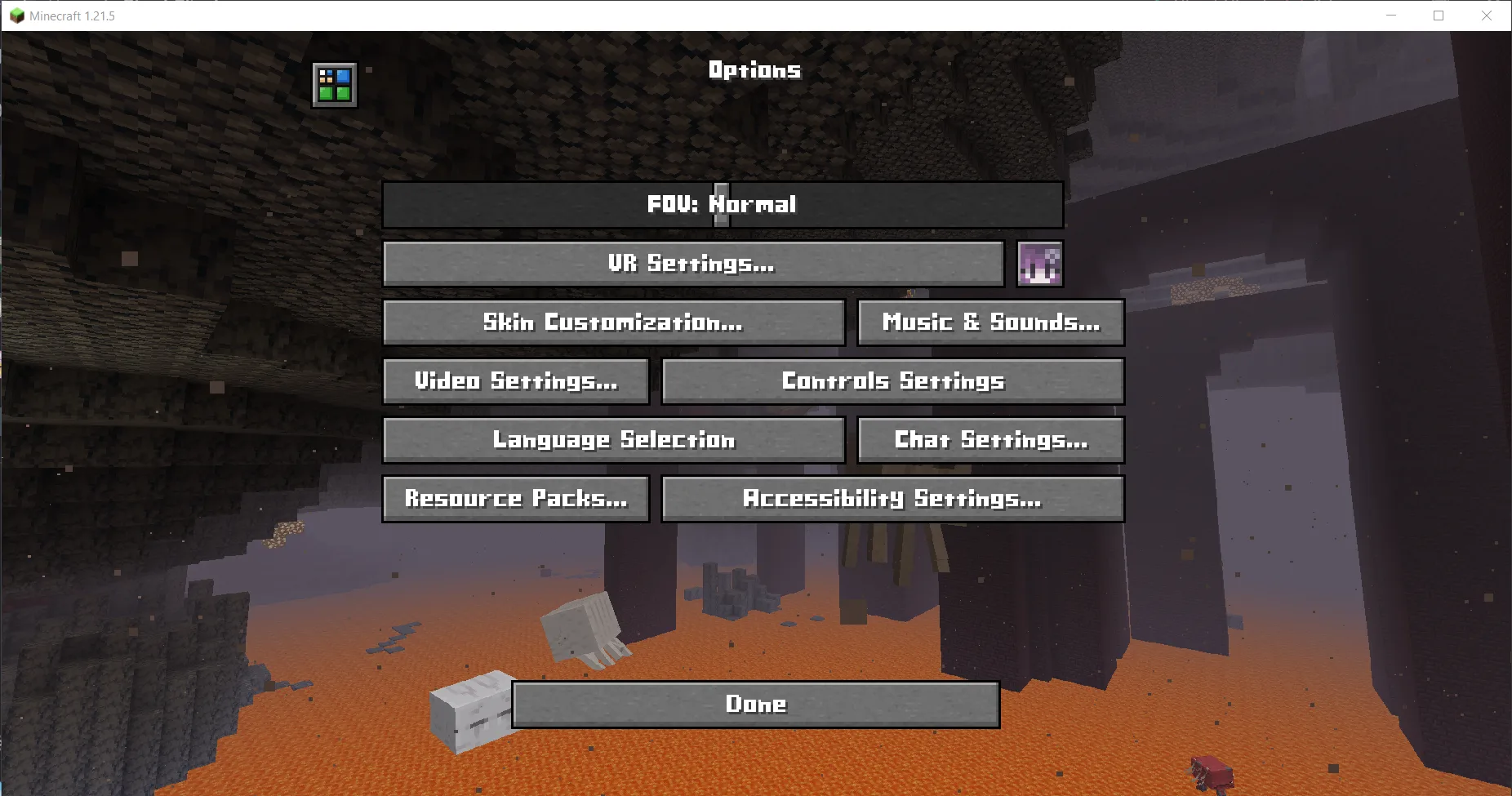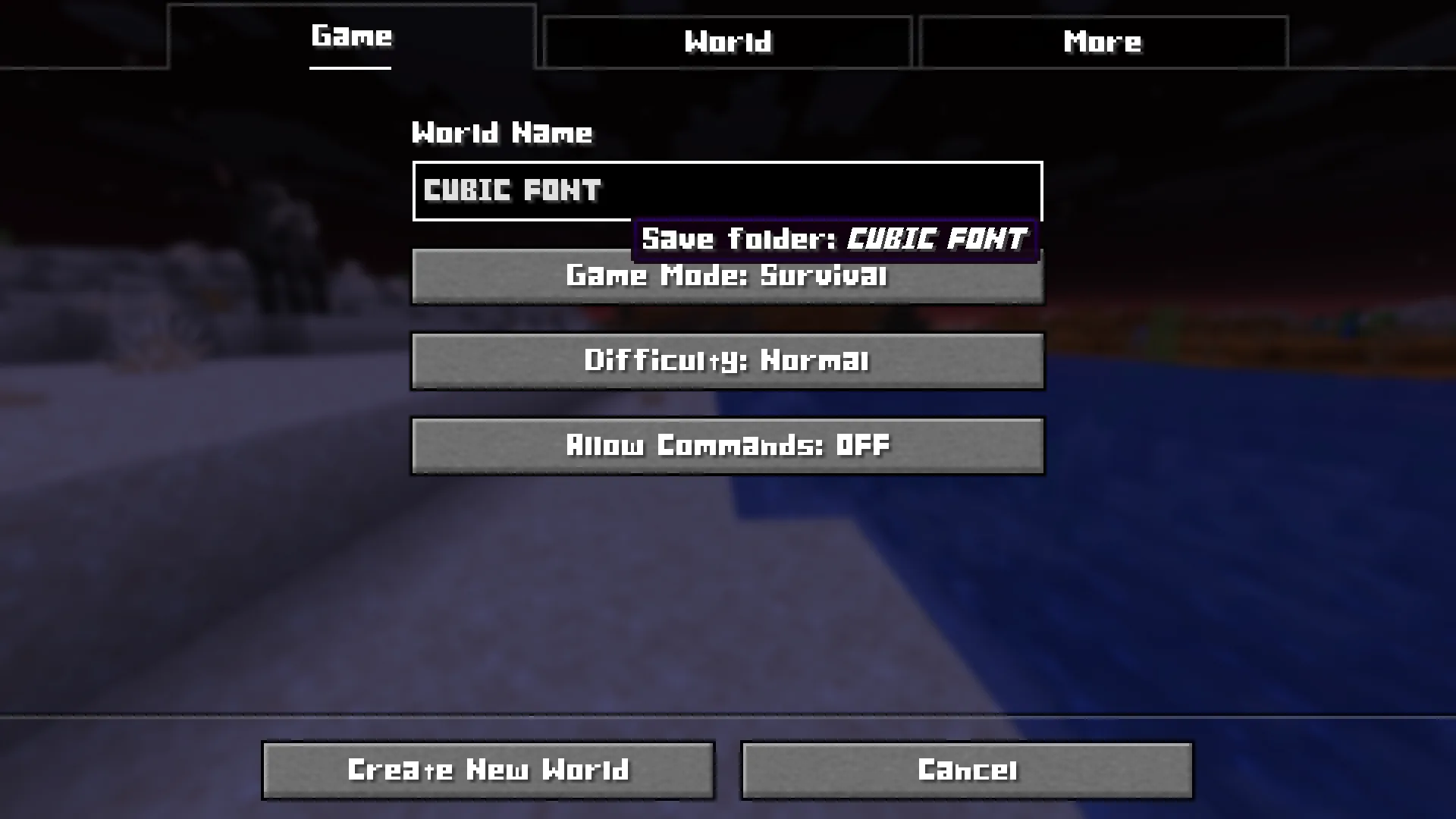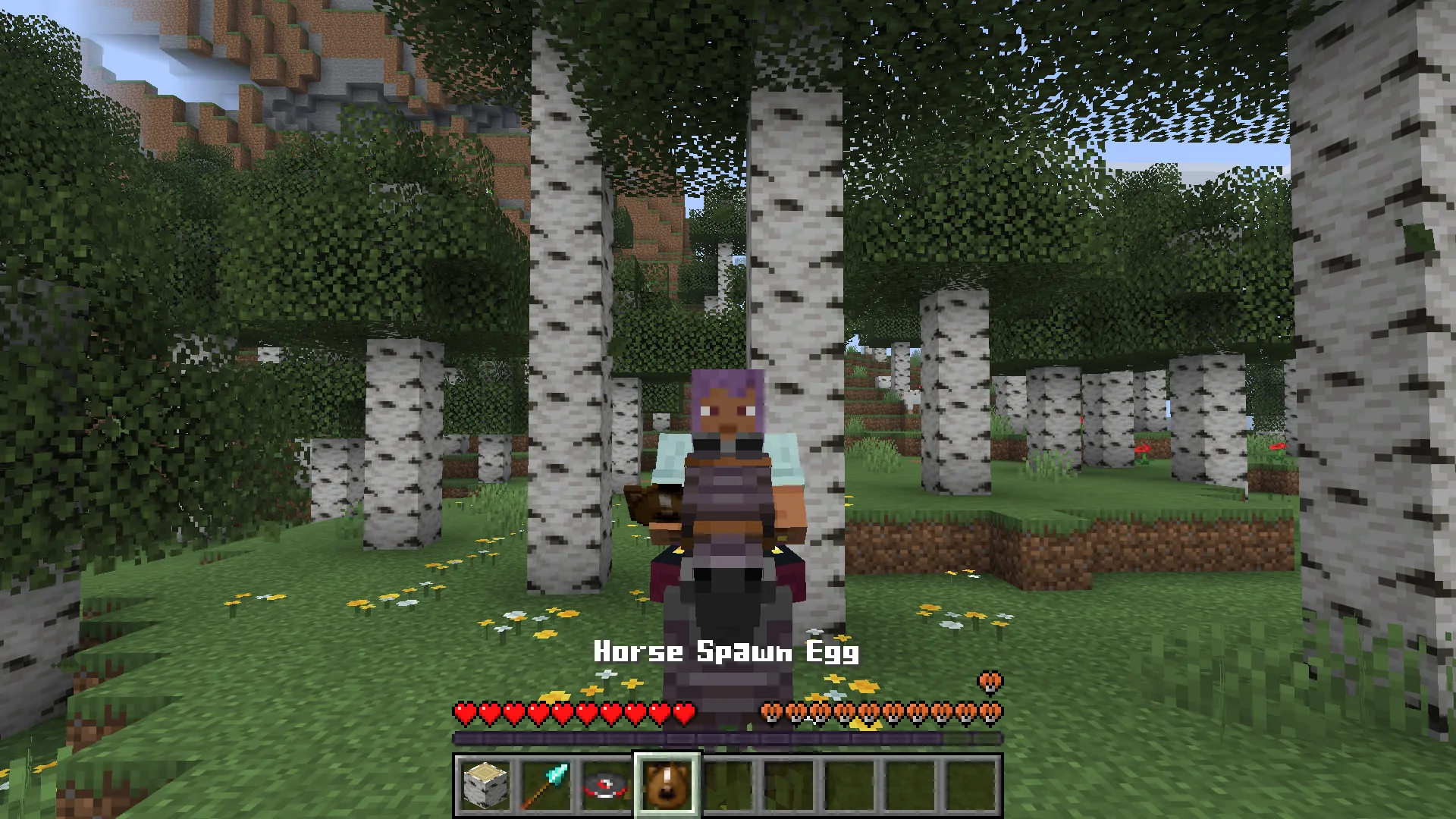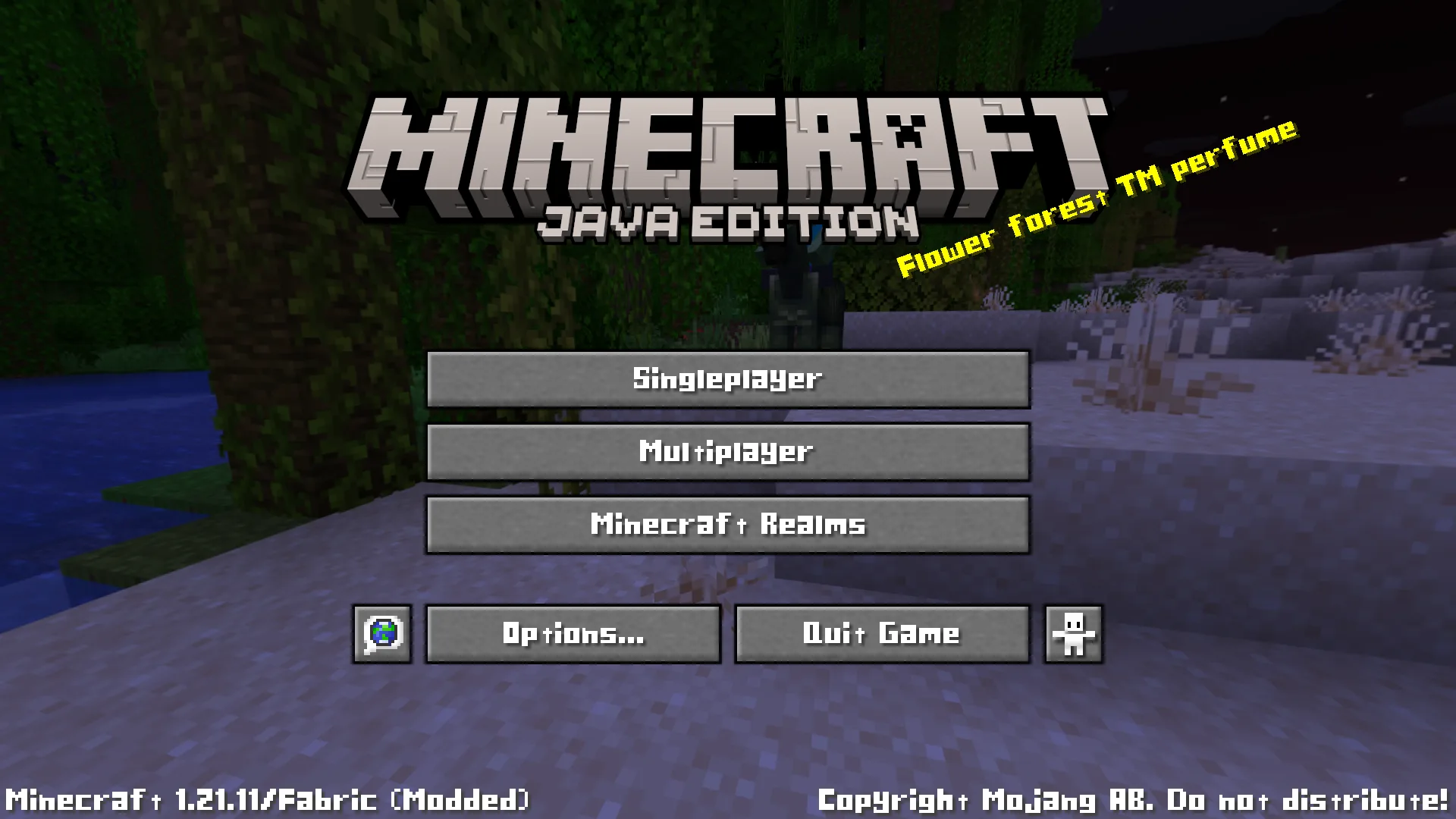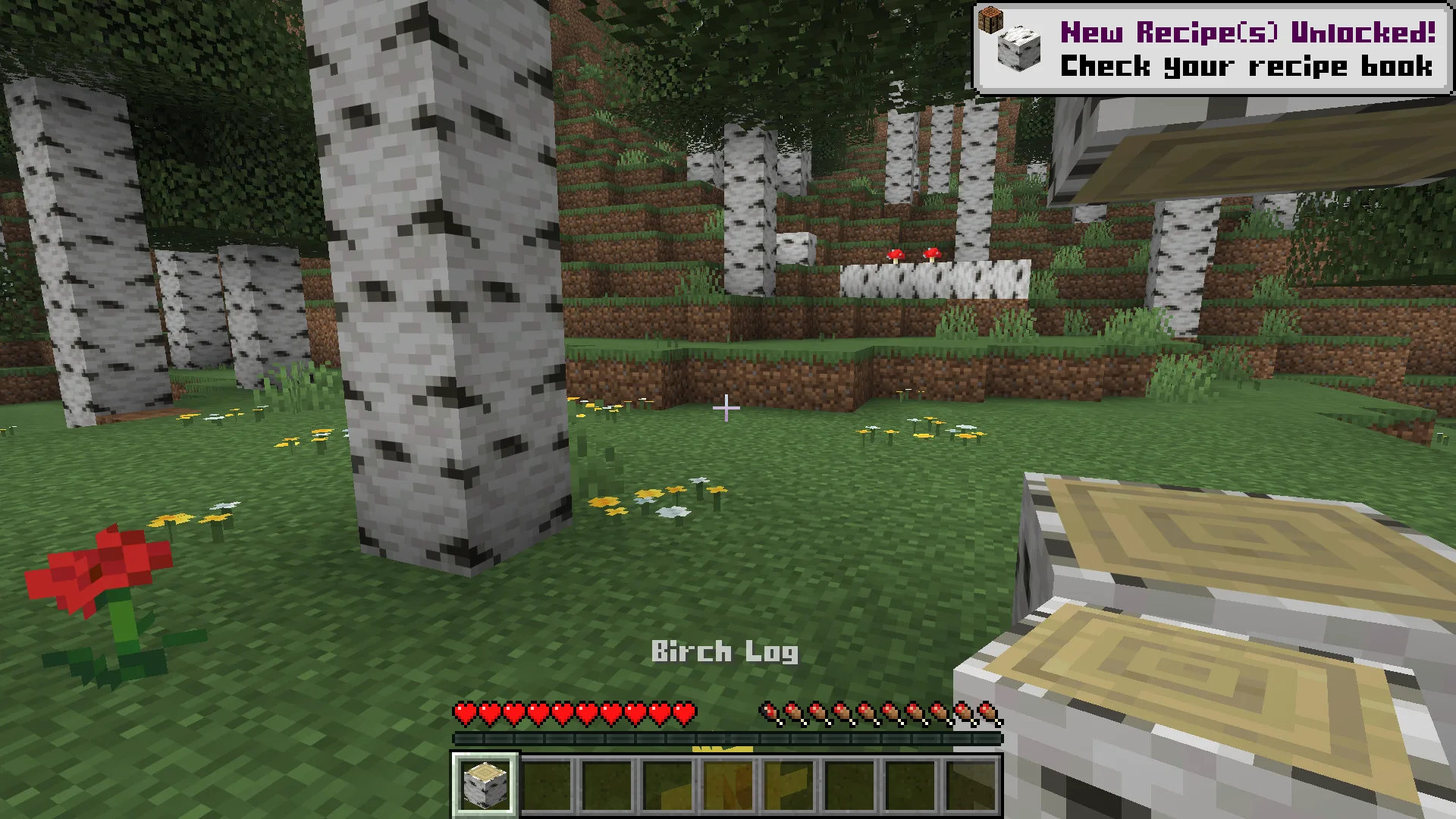
Cubic Font
Кубический шрифт заменяет стандартный шрифт Minecraft на геометрический, пиксельно-идеальный дизайн. Подходит для ванильной игры и модпаков.
Этот ресурспак заменяет стандартный шрифт Minecraft на смелый, чистый и блочный шрифт с геометрическим, пиксельно-идеальным дизайном. Шрифт идеально вписывается в блочную эстетику игры, одновременно улучшая чёткость и читаемость текста.